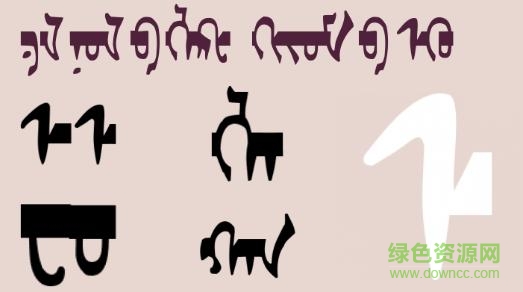
蒙文字體mongolf1免費(fèi)版
mongolf1字體免費(fèi)版是一款實(shí)用的蒙文字體,字形美觀,可應(yīng)用于蒙文網(wǎng)站設(shè)計(jì),本站還為廣大字體愛好者提供了超多精美的英文無襯線字體襯線字體,有需要者歡迎在綠色資源網(wǎng)下載!
蒙文字體mongolf1
蒙文字體演變歷程
蒙文字是經(jīng)過腓尼基字母--- 阿拉米字母 --- 粟特字母 --- 畏兀兒字母這樣一個(gè)漫長的演變過程的。它從上到下連寫(一個(gè)單詞為一個(gè)單位),從左到右移行。